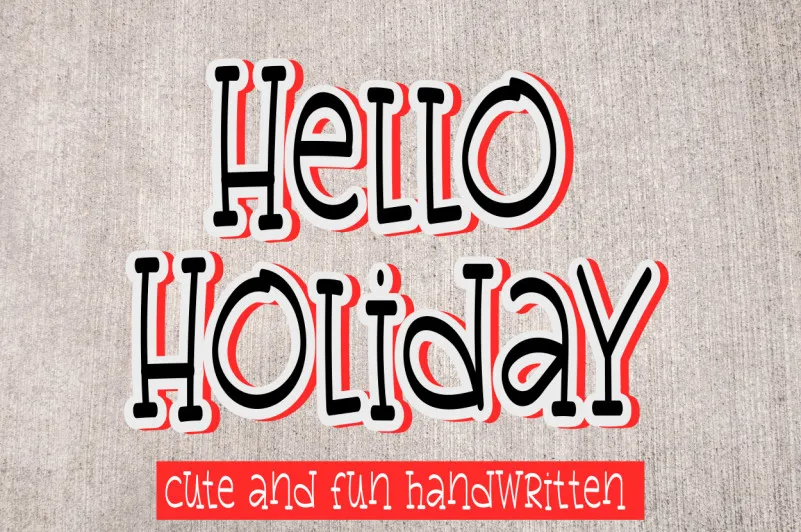
Hellow Holiday Font – Download Grátis
Esta fonte exótica e simpática se destaca nas categorias de display fonts por sua versatilidade. Seja ela usada para designs relacionados a bonequinhos, jogos infantis ou qualquer projeto que precise de um toque encantador, esta font será uma escolha incrivelmente brilhante. Sujeito à criatividade e aos estilos coloridos desta fonte, o resultado final certamente trará aquele elemento especial que faz a diferença no design. A sugiharto1790 trouxe para nós um pedaço de pura diversão e originalidade, garantindo uma experiência visual inesquecível em qualquer projeto.
Designer: sugiharto1790